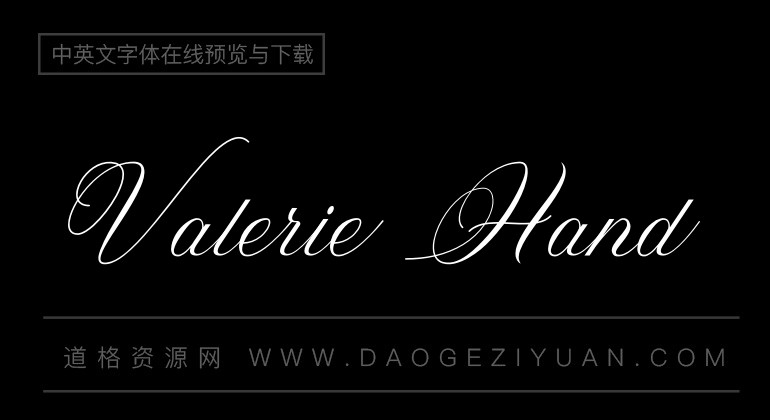
Valerie Hand
Valerie Hand 字体是一款英文手写字体,由英国设计师Valerie 创作。它是一款具有现代风格的英文手写字体,带有明显的曲线和流畅的线条,在设计上,它具有自然、温暖的感觉。它可以用于各种印刷品,包括海报、书籍、标志、标牌等,也可以用于网页和社交媒体上的文字。它的字形具有自然的韵律和活力,可以为设计师提供更多的创意空间,让他们的设计更具有个性。
Valerie Hand是一款非常不错的手写艺术字体,具有很好的视觉感,适合于文化类的宣传设计、商业类品牌的广告和产品包装设计以及个性化文字排版等较多场景。
Valerie Hand字符映射图